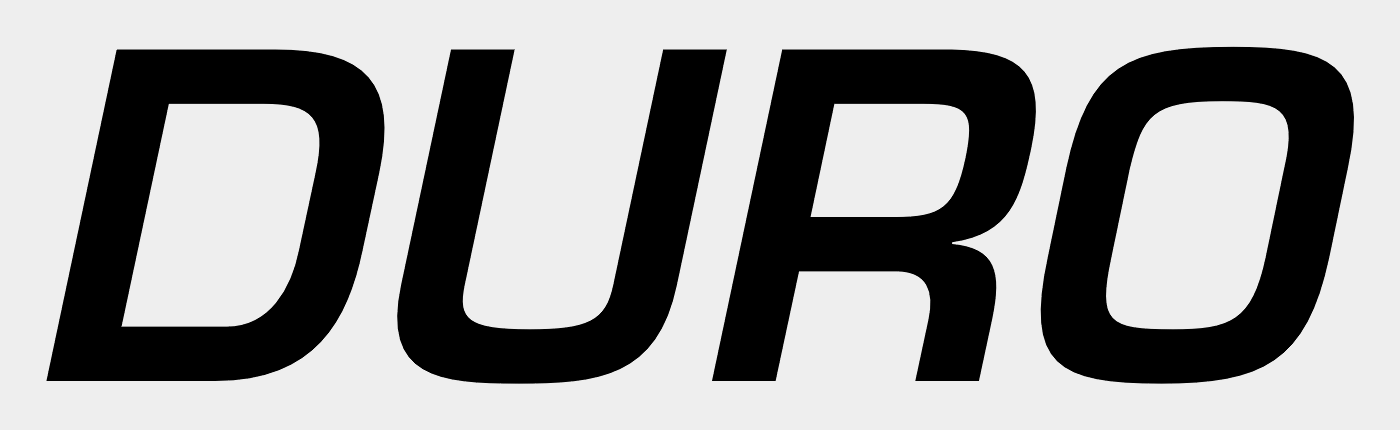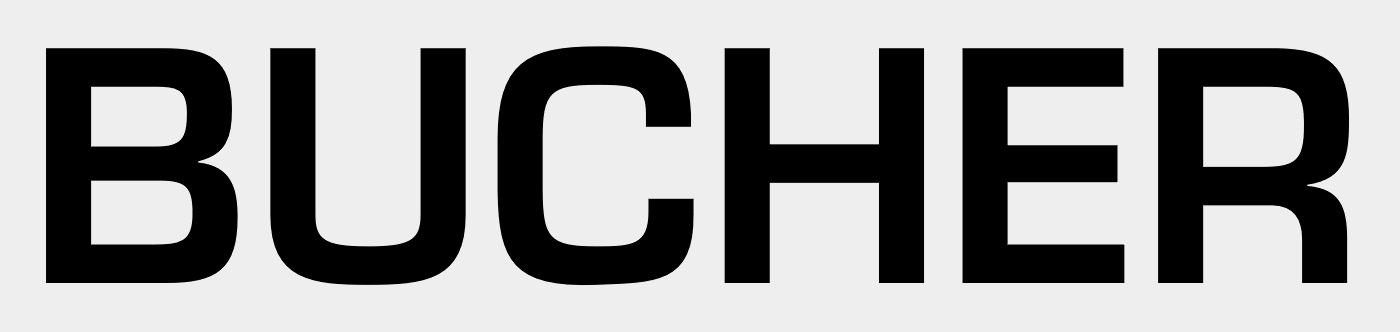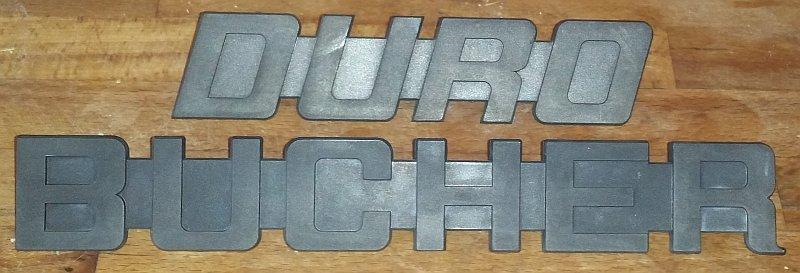
Schriftart von Bucher (Schweizer Fahrzeughersteller) gesucht
Ich bin auf der Suche nach der Schriftart die die Schweizer Firma BUCHER verwendet, insbesondere für die beschriftung des DURO.
So wie ich das sehe könnten das unter Umständen auch 2 etwas verscheidene aber sehr ähnliche Schriftarten sein.
(Der Fuß vom R ist bei BucheR sehr charakteristisch gebogen, in der kursiven Variante ist er gerade.)
Schade, ich hatte doch ein bissel auf die Faulheit des Herstellers und damit auf eine Standartschriftart gehofft.
Eurostile ist zwar ähnlich aber auch "Nur ähnlich".
Da werd ich wohl nicht umhinn kommen mir das selbst zu zeichnen.
Nun, in diesem Fall liegst du mit der "Faulheit des Herstellers" wohl richtiger, als du denkst, denn diese Schilder entstammen sicherlich einer Zeit vor digitalen Vektorschriften. Und da war es einfach weit einfacher, dem Modellbauer die schrift frei sdrauflos zeichnen tzu lassen, ls eine Bleisatzschrift originalgetreu nachzuzeichnen.
Es sind doch eigentlich erst läppische 2 Jahrzehnte, in denen praktisch jeder stets auf ein riesiges Angebot an Schriftarten zugreifen kann. Davor gab es einige Zeit Letraset-Bögen, die einem für Entwürfe scghon ein größeres Angebot an Schriften boten, die mann dann fotografisch auch vergößern konte, und davor war Handarbeit nach Vorlagen in Büchern angesagt. Da hat man natürlich vereinfacht, wo es geht.
Dem kann ich jetzt nur bedingt zustimmen, nämlich für die Firma Bucher, die gibts sicher schon seit der Zeit von Letraset, wenn nicht noch länger. Wie sich deren Logo über die Zeit entwickelt hat weiß ich leider nicht.
Die Marke "Duro" wurde aber erst 1994 erfunden, die Schilder selbst stammen von 2002, sind also noch garnicht soooo alt.
Und eben 1994 war noch eine Zweit, in der CAM noch sehr in nen Kinserschuhemn steckte. Meine Konstruktionen, die ich damals per AutoCAD schon machte, mussten noch geplottet, und als Zeichnungen an die Modellbauer gehen, die dann die Formmodelle komplett von Hand erstellewn. Auch verwendeten die CAD-Programme dieser Jahre noch keine Standardschriften, dondern Mittellinien-Schriften, deren Buchsataben aus vielen kleinen geraden Linienabschnitten destanden,, die Standardschrift war also sehr eckig,  Wenn diese Schilder 2002 hergestellt wurden, dann sicherlich nach den alten Modellen.